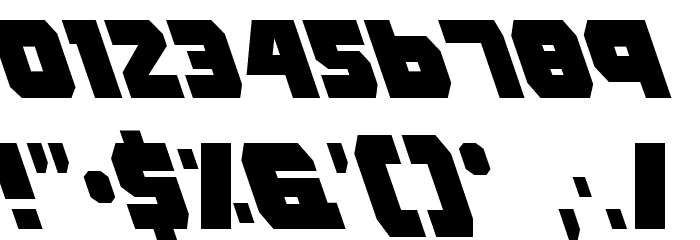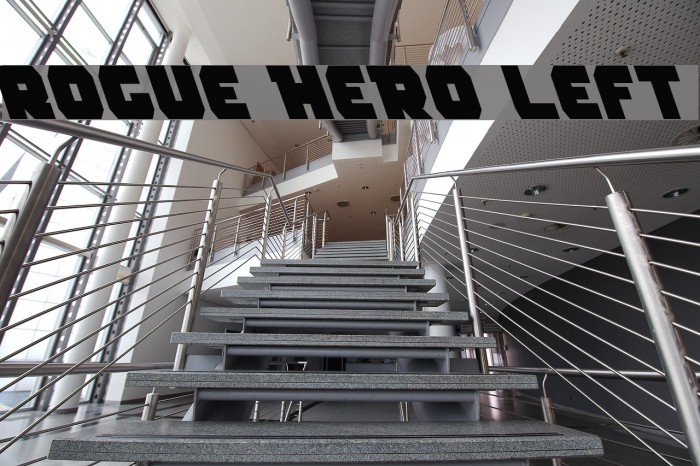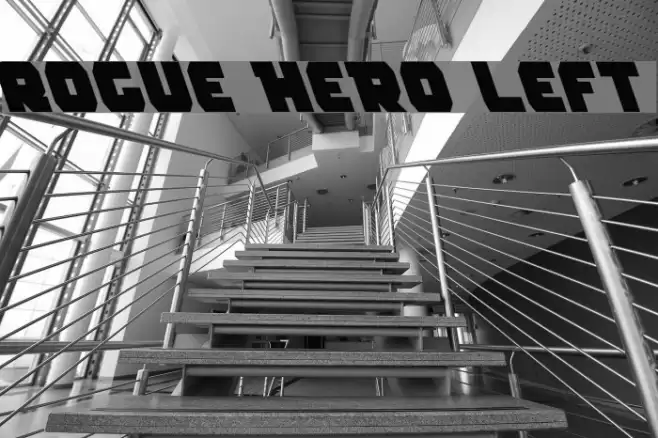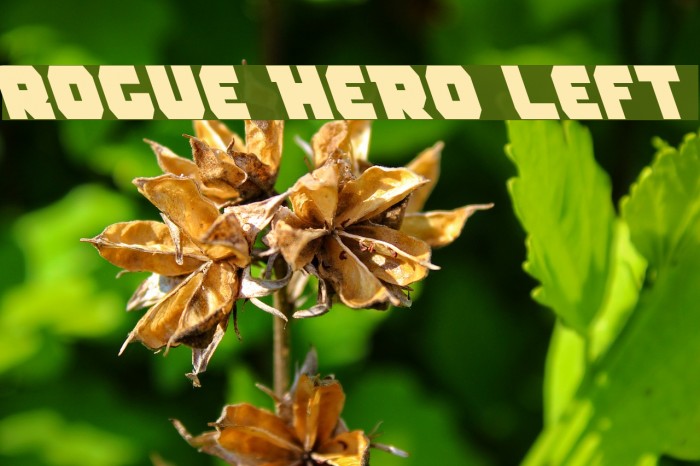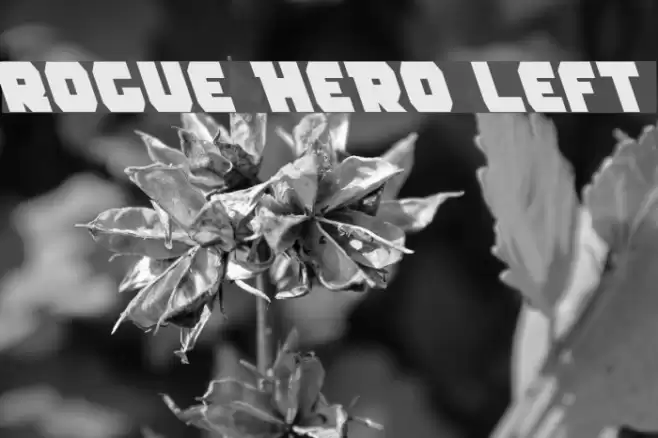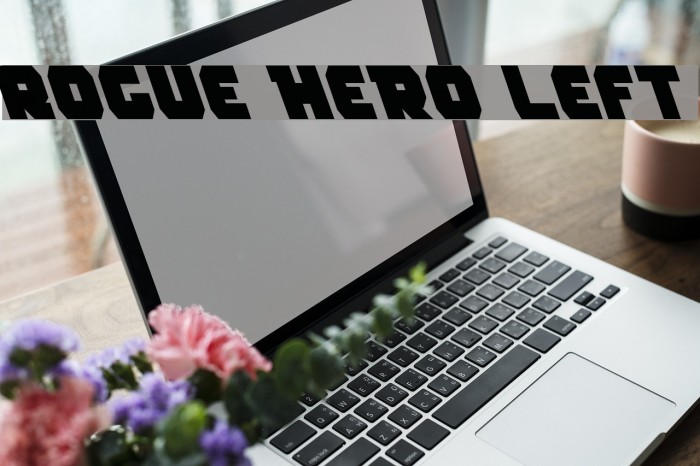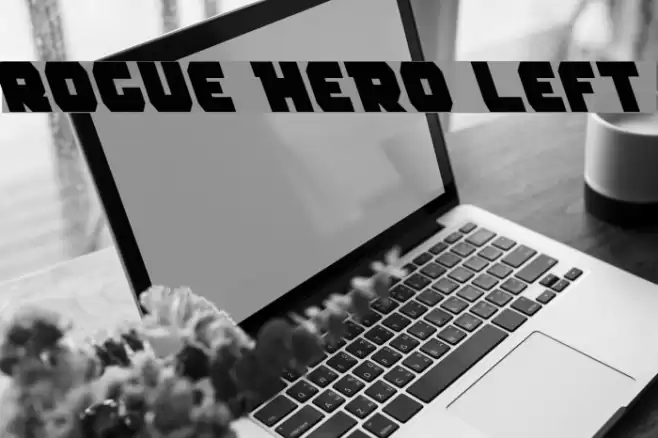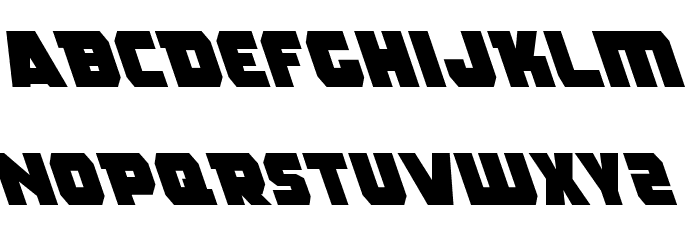
Rogue Hero Left Font
| 全体的なスタイル | Futuristic, Dynamic |
| おすすめプロジェクト | Ideal for video game titles, movie posters, or any project requiring a bold, futuristic aesthetic. |